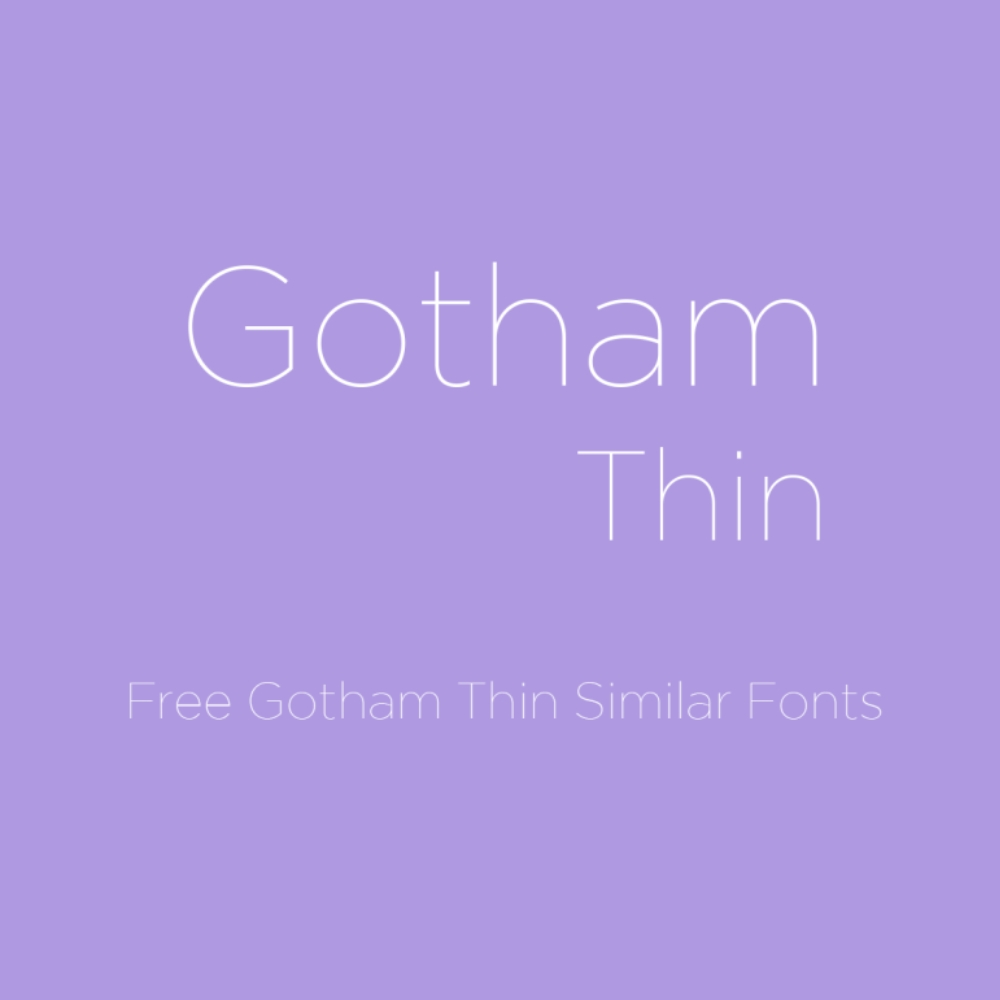
Download font Gotham là lựa chọn lý tưởng cho những thiết kế cần thể hiện phong cách hiện đại, mạnh mẽ và đậm chất đô thị. Với đặc trưng geometric rõ ràng, Gotham giúp thương hiệu tạo dấu ấn chuyên nghiệp và năng động trong mắt khách hàng.
Font Gotham là gì?
Font Gotham được thiết kế năm 2000 bởi Tobias Frere-Jones tại foundry Hoefler & Co. (trước đây là Hoefler & Frere-Jones). Font này lấy cảm hứng từ các biển hiệu kiến trúc ở New York thời đầu-giữa thế kỷ 20, đặc biệt là chữ khắc trên Port Authority Bus Terminal.
Gotham trở nên nổi tiếng toàn cầu nhờ chiến dịch tranh cử tổng thống của Barack Obama năm 2008 với slogan “Change” và “Hope” được set bằng Gotham. Từ đó, font này trở thành biểu tượng của sự thay đổi, tiến bộ, hy vọng và được nhiều thương hiệu lớn áp dụng.
• GQ Magazine – tạp chí thời trang nam hàng đầu
• Spotify – nền tảng streaming nhạc
• Netflix – phần marketing và quảng cáo
• Coca-Cola – một số chiến dịch marketing
• Obama Campaign 2008 – chiến dịch tranh cử lịch sử
• Saturday Night Live – chương trình truyền hình
Các phiên bản Gotham:
• Gotham: Dòng chính với 8 weight từ Thin đến Ultra.
• Gotham Rounded: Phiên bản bo tròn các góc, thân thiện hơn.
• Gotham Narrow: Phiên bản thu hẹp, tiết kiệm không gian.
• Gotham Condensed: Phiên bản condensed cho tiêu đề hẹp.
• Gotham XNarrow: Phiên bản extra narrow.
Mỗi dòng có nhiều weight: Thin, Extra Light, Light, Book, Medium, Bold, Black, Ultra.
Font thay thế Gotham miễn phí
Các font miễn phí từ Google Fonts có phong cách rất giống Gotham:
• Montserrat (Google Fonts): Font geometric giống Gotham đến 95%, với 18 weight từ Thin đến Black. Hoàn toàn miễn phí và phổ biến nhất.
• Raleway (Google Fonts): Font elegant geometric, phong cách gần Gotham với 18 weight.
• Work Sans (Google Fonts): Font geometric mạnh mẽ như Gotham, với 9 weight.
• Nunito Sans (Google Fonts): Font rounded geometric, tương tự Gotham Rounded.
• Outfit (Google Fonts): Font geometric hiện đại, gần với Gotham.
So sánh font thay thế với Gotham:
Font Gotham với nét chữ hiện đại
Ứng dụng font Gotham trong bao bì thời trang
Font Gotham mang phong cách geometric mạnh mẽ, đô thị, được ưa chuộng trong ngành thời trang và lifestyle:
• Geometric mạnh mẽ, đô thị: Gotham lấy cảm hứng từ biển hiệu New York, tạo cảm giác đô thị, hiện đại, năng động – phù hợp thương hiệu thời trang streetwear, urban fashion.
• Trung tính nhưng có tính cách: Khác với Helvetica quá trung tính, Gotham có chút tính cách riêng (góc vuông, nét đậm) nhưng vẫn đủ linh hoạt cho nhiều thương hiệu.
• Phù hợp thương hiệu trẻ, năng động: Font Gotham tạo hình ảnh thương hiệu trẻ trung, tiến bộ, thay đổi – lý do Obama chọn nó cho “Change”.
• Kết hợp tốt với hình ảnh đô thị: Gotham kết hợp hoàn hảo với ảnh đường phố, kiến trúc thành phố, phong cách urban lifestyle.
Font Gotham xuất hiện trong nhiều sản phẩm in ấn thời trang:
• Bao bì thời trang: hộp giày, hộp quần áo, hộp phụ kiện cao cấp.
• Túi giấy thời trang: túi kraft, túi couche cho brand thời trang urban, streetwear.
Gotham là font chữ mang đậm tinh thần hiện đại và đô thị, rất phù hợp cho các thiết kế cần sự nổi bật và chuyên nghiệp. Nếu chưa có điều kiện sử dụng bản quyền, bạn hoàn toàn có thể thay thế bằng các font miễn phí như Montserrat hay Raleway mà vẫn đảm bảo tính thẩm mỹ.